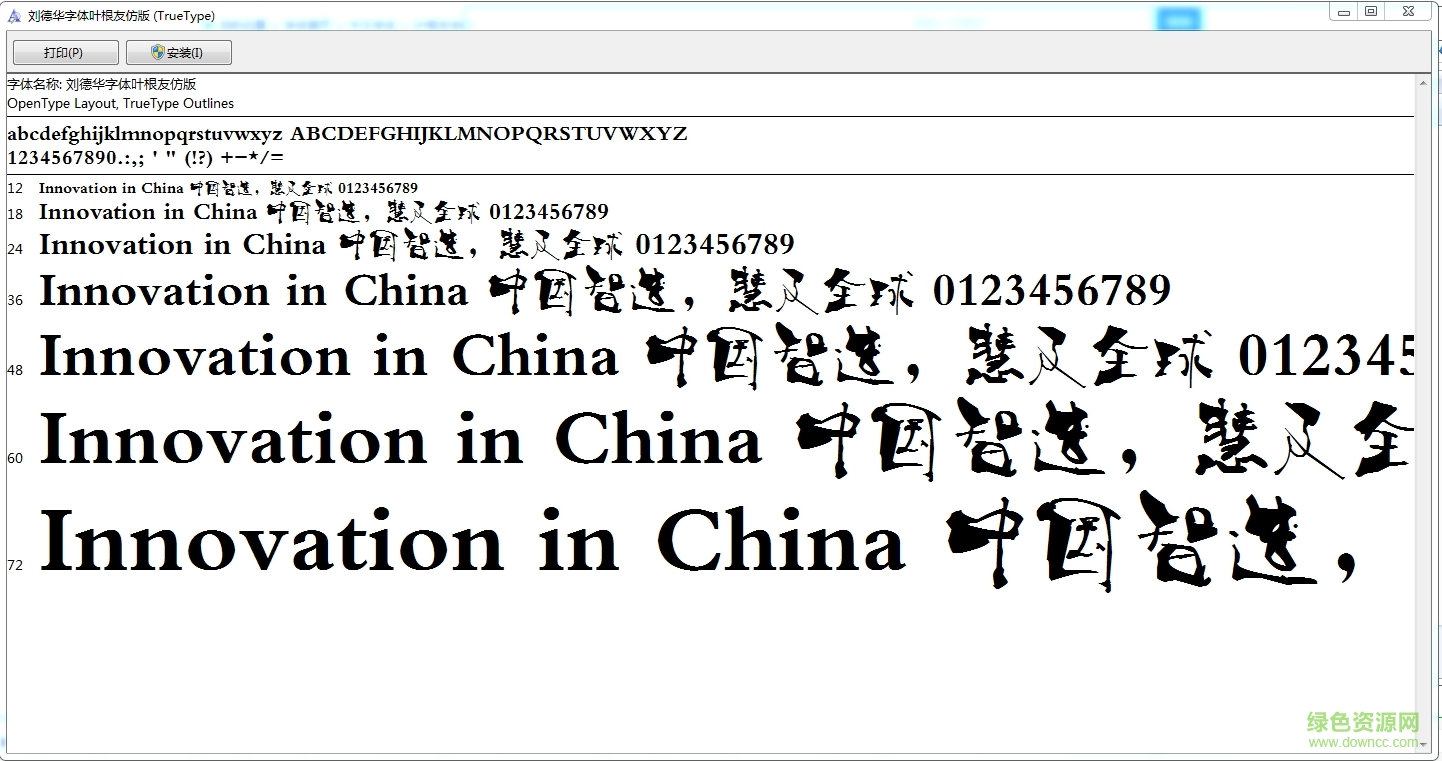
葉友根仿劉德華字體是書(shū)法大家葉友根先生模仿香港影星劉德華先生的一個(gè)字體。劉德華的粉絲們有福了,字體模仿的清新自然,字體優(yōu)美,實(shí)用性強(qiáng),是一款彰顯自身個(gè)性,或者用于平面設(shè)計(jì)的藝術(shù)字體。喜歡的小伙伴快來(lái)綠色資源網(wǎng)下載吧!